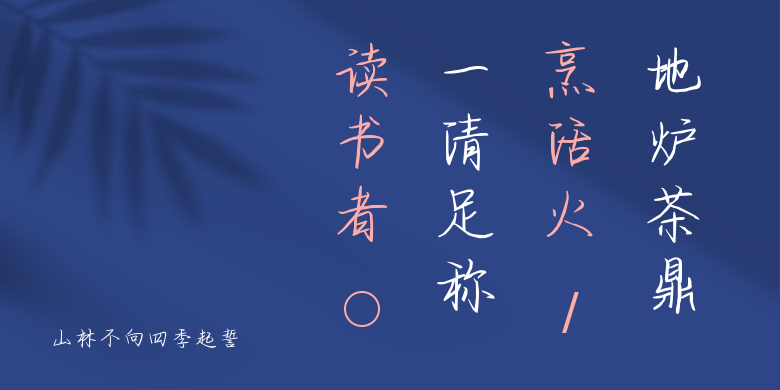
山林不向四季起誓
山林不向四季起誓,这款字体结构工整、笔画清晰,兼顾美观与易读性,适用于标题、正文、海报、包装、LOGO 等多种场景。字形优雅稳定,风格百搭耐看,适配日常排版与创意设计,让文字呈现更舒适、更具质感。山林不向四季起誓一笔一画,皆是细节,以均衡的比例、流畅的线条打造舒适视觉体验,字形端正大气,风格简约现代。无论是商业设计、品牌宣传还是日常排版,都能轻松驾驭,让文字更有格调与力量。山林不向四季起誓字体下载。